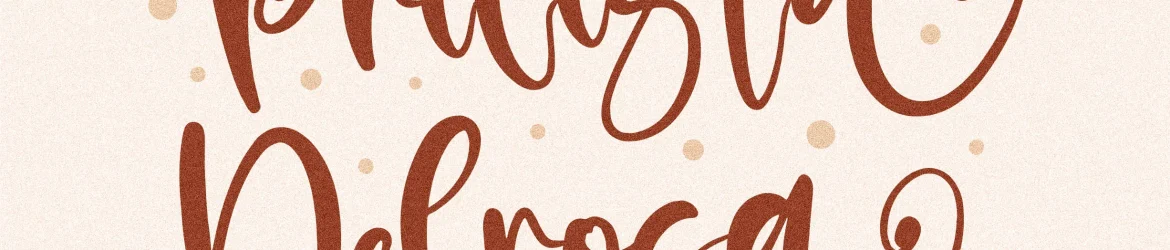
Prilista Delrosa Font – Download Grátis
A fonte “Prilista Delrosa” é uma tipografia escrita a mão que se destaca em projetos variados, desde logotipos e campanhas de marca até designs para embalagens de produtos e sacolas de shopping. Suas linhas fluidas e suavidades naturais tornam essa fonte uma escolha perfeita para criações de luxo. De ideias memoráveis como cartões de convite e selos personalizados aos detalhes atraentes em fotografias, sua elegância e delicadeza enriquecem qualquer projeto. As vantagens não param aqui; com “Prilista Delrosa”, você pode trazer uma nuance única à sua identidade visual ou design gráfico, dando vida ao seu trabalho de forma autêntica e sofisticada.